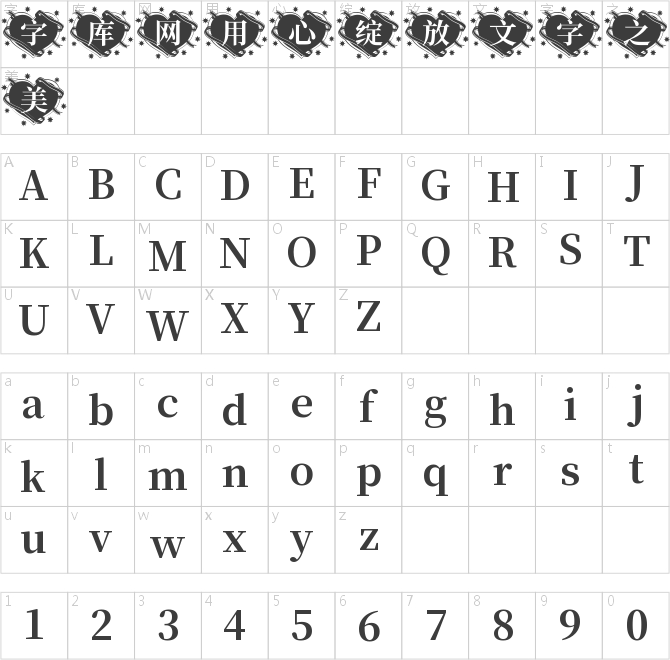
這個字體是在“思源宋體 粗體”基礎上提取英文與符號共123個字形,漢字6763個常用字修改而成,所謂花樣字體,筆者自定義為:給常規字形加一些修飾花紋效果。本次共享的花樣字體只對6763個漢字添加花紋,英文與符號保持原字形不變,大部分花樣字體并不適用于大篇幅的文章使用,主要作用于標題或一些特殊場合,如圖片水印等等。